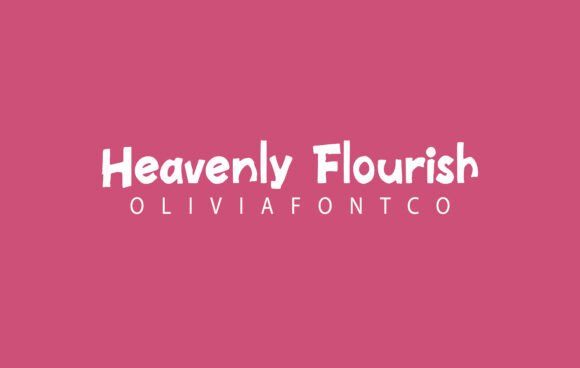
Heavenly Flourish
Heavenly Flourishのような高品質の素材をお探しの場合、このプレミアムパッケージはクリエイティブなプロジェクトに素晴らしい選択です。
POD(オンデマンド印刷)製品、結婚式の招待状、またはソーシャルメディアのグラフィックを作成している場合でも、Heavenly Flourishは理想的です。